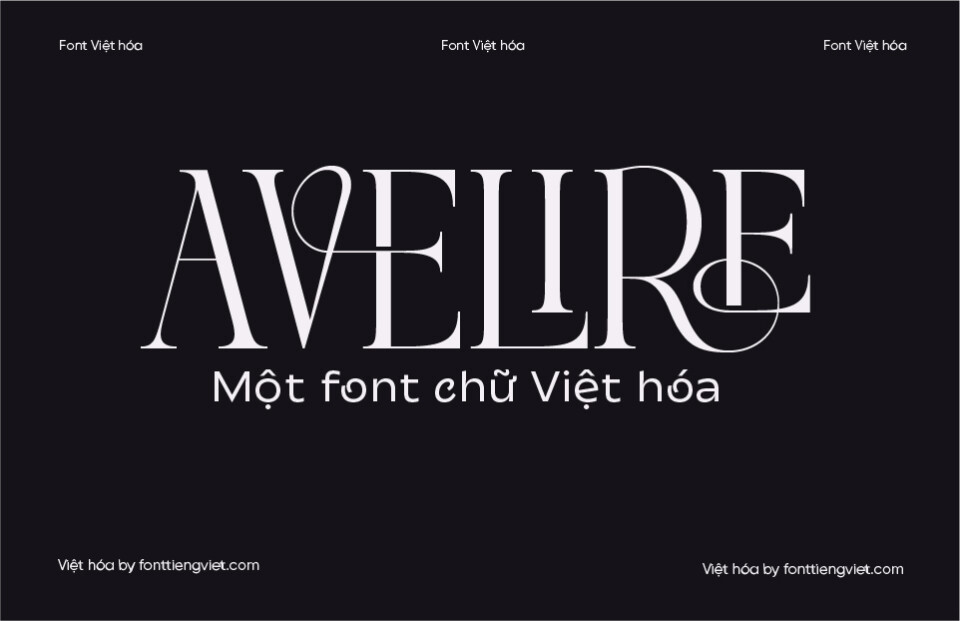
Font Việt hóa 1FTV VIP Avelire
Giới thiệu về bộ Font Việt hóa 1FTV VIP Avelire
Trong thế giới đồ họa hiện đại, việc lựa chọn phông chữ phù hợp đóng vai trò then chốt để tạo nên linh hồn cho tác phẩm. Một trong những cái tên đang làm mưa làm gió trong cộng đồng thiết kế chính là Font Việt hóa 1FTV VIP Avelire. Đây là một bộ font mang phong cách serif cổ điển nhưng được cách tân mạnh mẽ với các đường nét thanh mảnh, uốn lượn tinh tế. Đối với những bạn đang tìm kiếm Font Miễn Phí để làm mới kho tài nguyên của mình, 1FTV VIP Avelire chính là sự lựa chọn không thể bỏ qua nhờ khả năng ứng dụng linh hoạt trong nhiều lĩnh vực khác nhau.
Đặc điểm nổi bật của Font Việt hóa 1FTV VIP Avelire
Điểm thu hút nhất của bộ font này chính là sự cân bằng giữa tính thẩm mỹ và khả năng đọc. Các ký tự được chăm chút tỉ mỉ, giúp nội dung không chỉ đẹp mắt mà còn rất chuyên nghiệp. Việc 1FTV VIP Avelire được Việt hóa hoàn chỉnh giúp người dùng tại Việt Nam dễ dàng gõ các dấu tiếng Việt mà không lo lỗi hiển thị. Đây là ưu điểm lớn cho các bạn học sinh, sinh viên khi thực hiện các dự án thuyết trình hoặc làm báo cáo trường học cần sự chỉn chu và độc đáo.
Ứng dụng thực tế của Font Việt hóa 1FTV VIP Avelire
Với vẻ ngoài sang trọng và đầy tính nghệ thuật, Font Việt hóa 1FTV VIP Avelire thường xuyên xuất hiện trong các thiết kế thương hiệu cao cấp. Bạn có thể dễ dàng bắt gặp bộ font này trên các bao bì mỹ phẩm, bìa tạp chí thời trang hay các thiệp mời sự kiện quan trọng. Ngoài ra, nhờ bộ ký tự thay thế (alternates) phong phú, các nhà thiết kế có thể sáng tạo ra những logo độc bản chỉ với vài thao tác tùy chỉnh đơn giản.
Tại sao nên sử dụng Font Việt hóa 1FTV VIP Avelire trong học tập
Trong môi trường giáo dục, việc trình bày nội dung một cách khoa học và đẹp mắt sẽ giúp học sinh ghi điểm cao hơn trong mắt thầy cô. Sử dụng Font Việt hóa 1FTV VIP Avelire cho tiêu đề bài viết hoặc các slide bài giảng sẽ giúp nội dung trở nên lôi cuốn và dễ tiếp thu hơn. Phông chữ này không quá cầu kỳ gây rối mắt, lại mang đến cảm giác tin cậy và nghiêm túc, rất phù hợp với các đề tài văn học hoặc lịch sử cần sự trang trọng nhất định.
Tổng kết về giá trị của Font Việt hóa 1FTV VIP Avelire
Có thể khẳng định rằng, đây là một bộ công cụ đắc lực cho bất kỳ ai yêu thích cái đẹp và sự hoàn mỹ trong con chữ. Font Việt hóa 1FTV VIP Avelire không chỉ dừng lại ở một phông chữ thông thường mà còn là nguồn cảm hứng sáng tạo vô tận. Việc sở hữu một bộ font đã được tối ưu tiếng Việt giúp tiết kiệm thời gian và nâng cao hiệu quả công việc rõ rệt. Đừng ngần ngại trải nghiệm ngay hôm nay để thấy được sự khác biệt mà nó mang lại cho các tác phẩm của bạn. Nếu bạn đang tìm kiếm các giải pháp thiết kế tối ưu, hãy truy cập Font Miễn Phí, Font Việt Hóa, Font Việt hóa 1FTV VIP Avelire để bắt đầu hành trình sáng tạo chuyên nghiệp nhất của mình nhé.